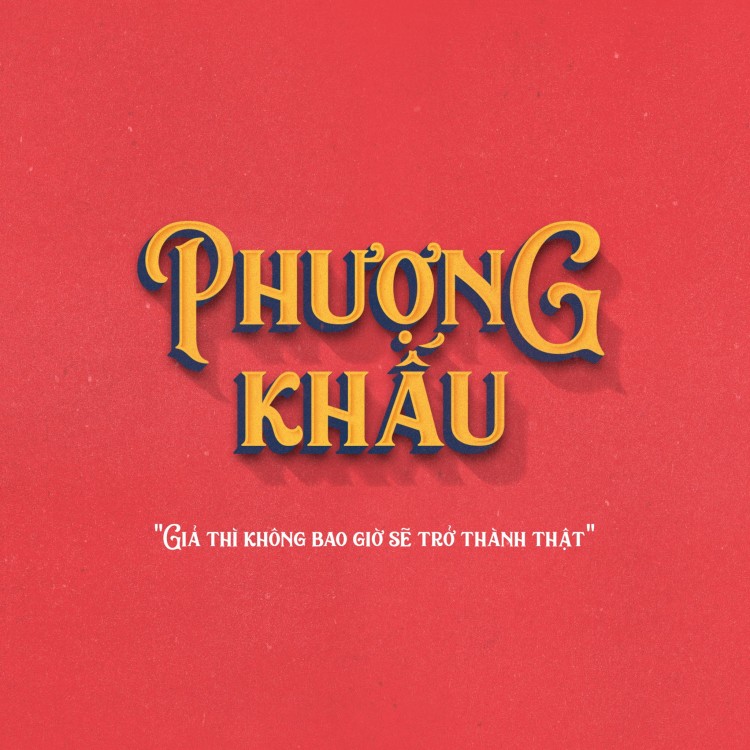
Giới thiệu bộ Font việt hóa LNTH Sacred Bridge cao cấp
Trong thế giới đồ họa hiện đại, việc lựa chọn Font Chữ phù hợp đóng vai trò quyết định đến tính thẩm mỹ của sản phẩm. Font việt hóa LNTH Sacred Bridge là một bộ phông chữ mang phong cách cổ điển, đậm chất nghệ thuật phương Tây nhưng vẫn giữ được nét thanh lịch cần thiết. Được lấy cảm hứng từ các bảng hiệu và nhãn hiệu từ thế kỷ 19, bộ phông này mang lại cảm giác hoài cổ, mạnh mẽ và vô cùng chuyên nghiệp. Phiên bản Việt hóa giúp các nhà thiết kế tại Việt Nam dễ dàng ứng dụng vào các dự án truyền thống hoặc hiện đại mà không lo lỗi dấu tiếng Việt.
Đặc điểm nổi bật của Font việt hóa LNTH Sacred Bridge
Phong cách thiết kế độc đáo và linh hoạt
Font việt hóa LNTH Sacred Bridge sở hữu những đường nét uốn lượn tinh tế cùng các ký tự thay thế đa dạng. Điều này cho phép bạn sáng tạo không giới hạn trong việc thiết kế logo, bao bì sản phẩm hoặc bìa sách. Phông chữ này không chỉ đơn thuần là các ký tự mà còn là một tác phẩm nghệ thuật, giúp thông điệp của bạn trở nên nổi bật và thu hút thị giác hơn bao giờ hết. Đặc biệt, bộ phông còn đi kèm các chi tiết trang trí đặc thù, tạo nên sự đồng nhất cho toàn bộ bản thiết kế.
Ứng dụng thực tế trong giáo dục và đời sống
Với các bạn học sinh và sinh viên, việc sử dụng phông chữ này trong các bài thuyết trình hay thiết kế báo tường sẽ giúp nội dung trở nên sinh động. Sự kết hợp giữa nét cổ điển và hiện đại giúp người xem dễ dàng tiếp nhận thông tin một cách thú vị hơn. Bộ phông này thực sự là công cụ hỗ trợ đắc lực cho những ai yêu thích sự sáng tạo và muốn thể hiện cá tính riêng qua từng trang viết.
Kết luận về bộ Font việt hóa LNTH Sacred Bridge